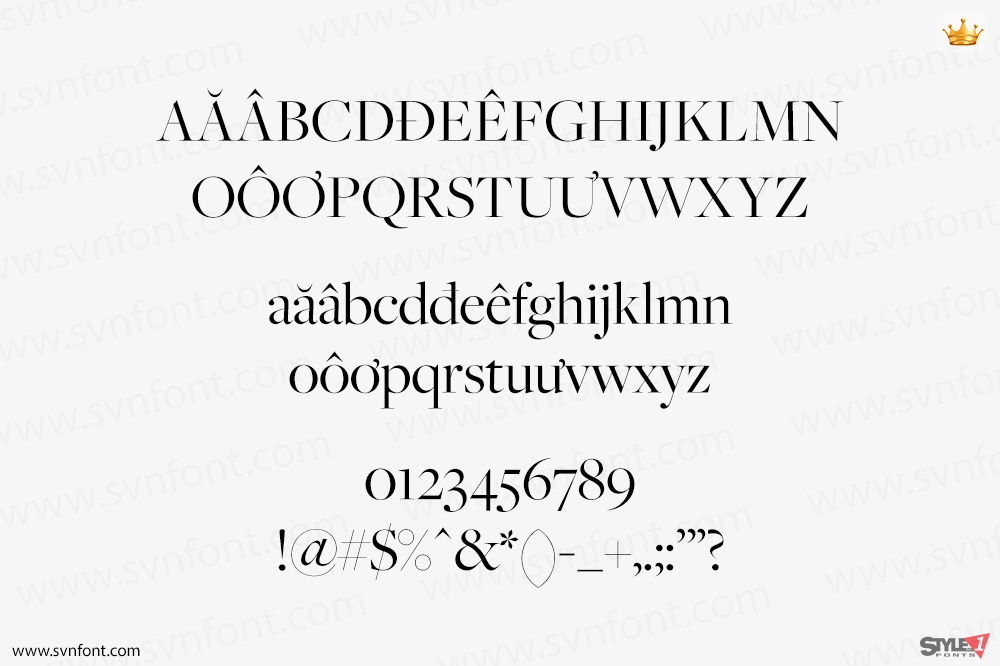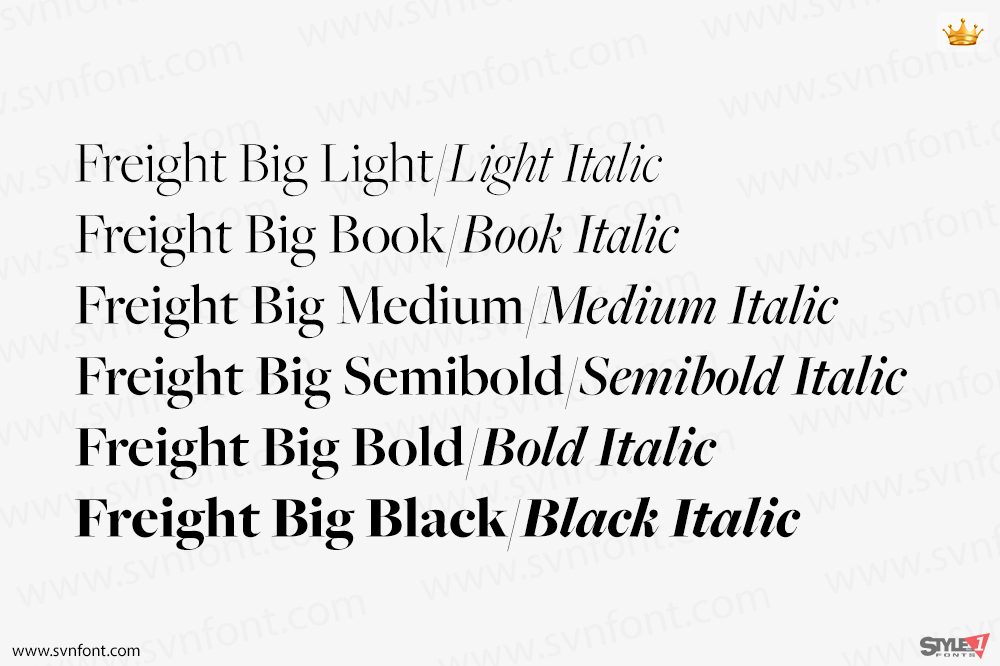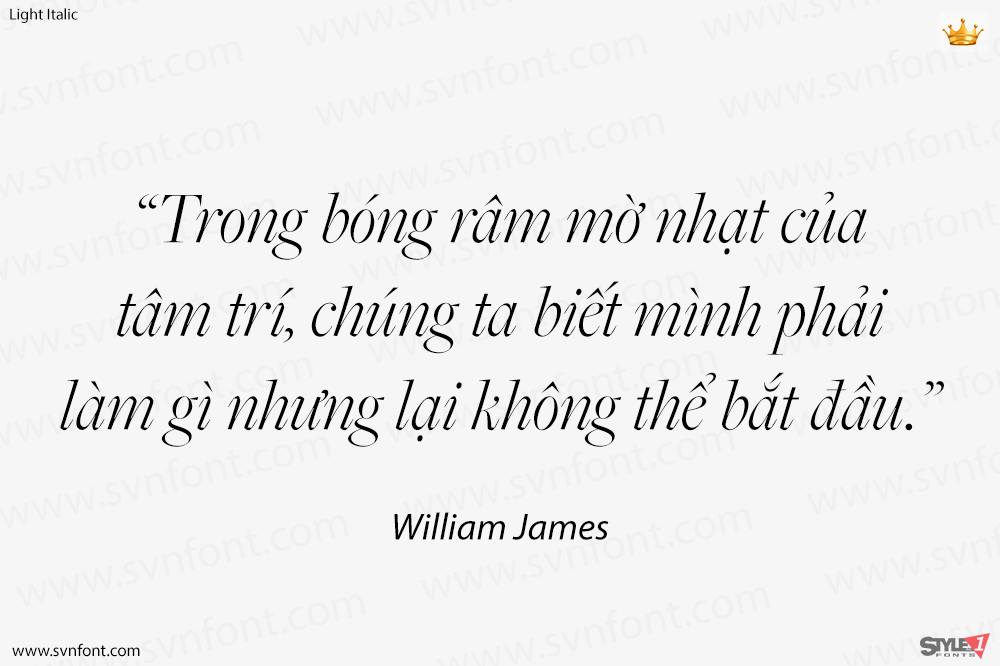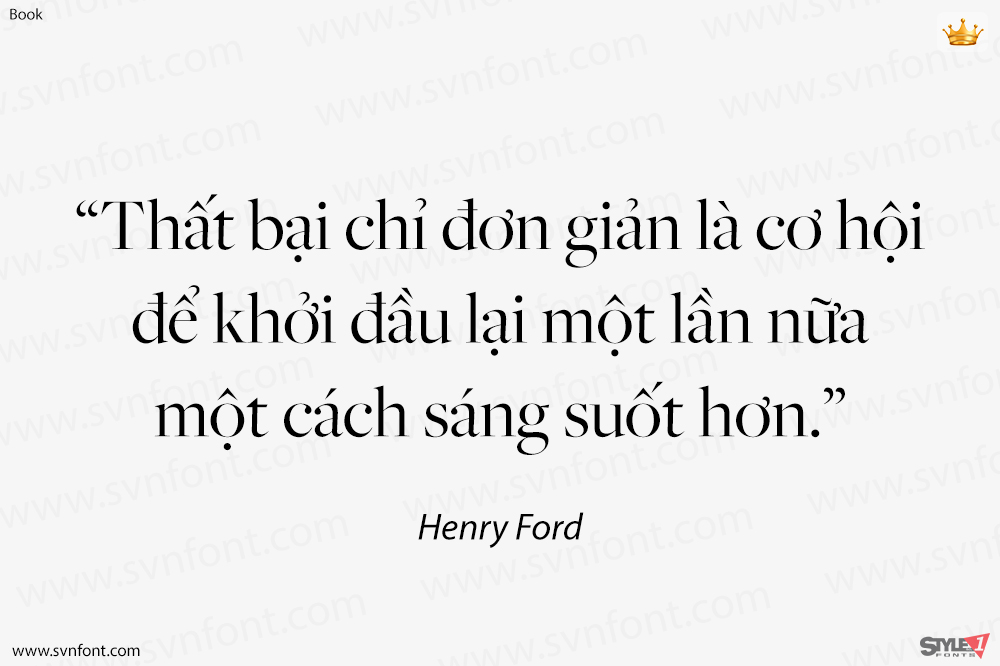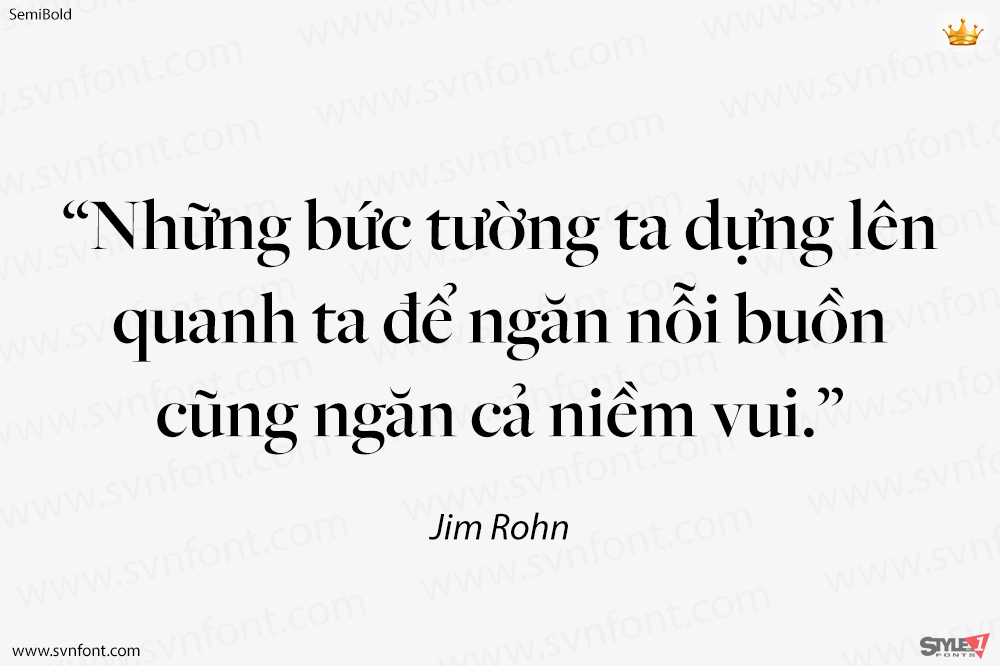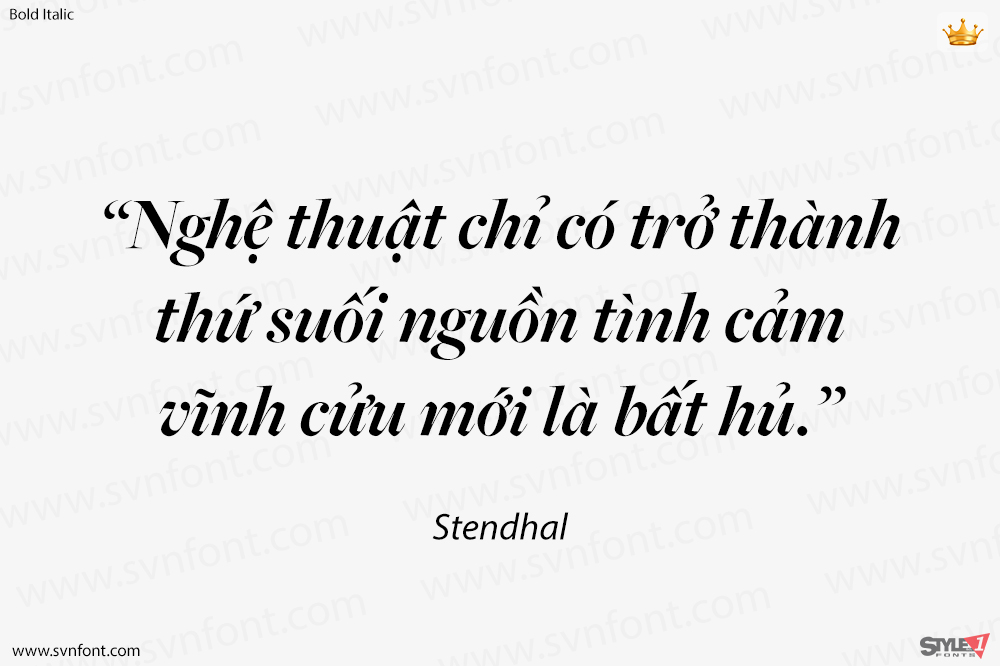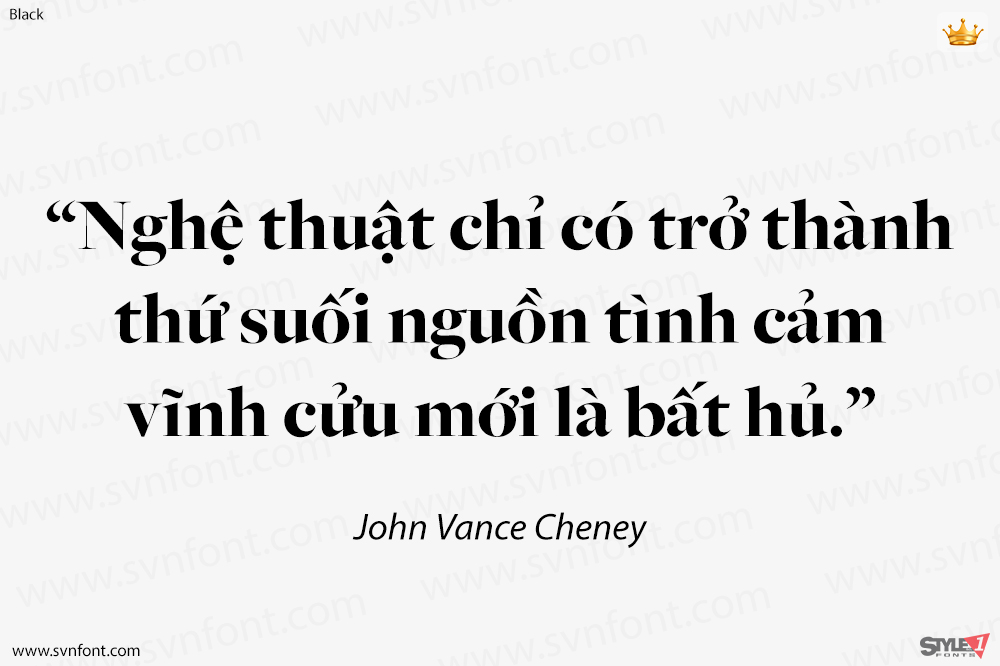
Freight Big là một phiên bản display của kiểu chữ Freight Text, được thiết kế để sử dụng ở các kích thước cực lớn. Họ phông chữ Freight đã bao gồm một phiên bản hiển thị có tên Freight Display, vì vậy Freight Big có độ tương phản cao hơn nữa và được thiết kế để sử dụng ở các kích thước lớn hơn nữa.
Nhà thiết kế: Joshua Darden
Nhà phát hành: The Freight Collection